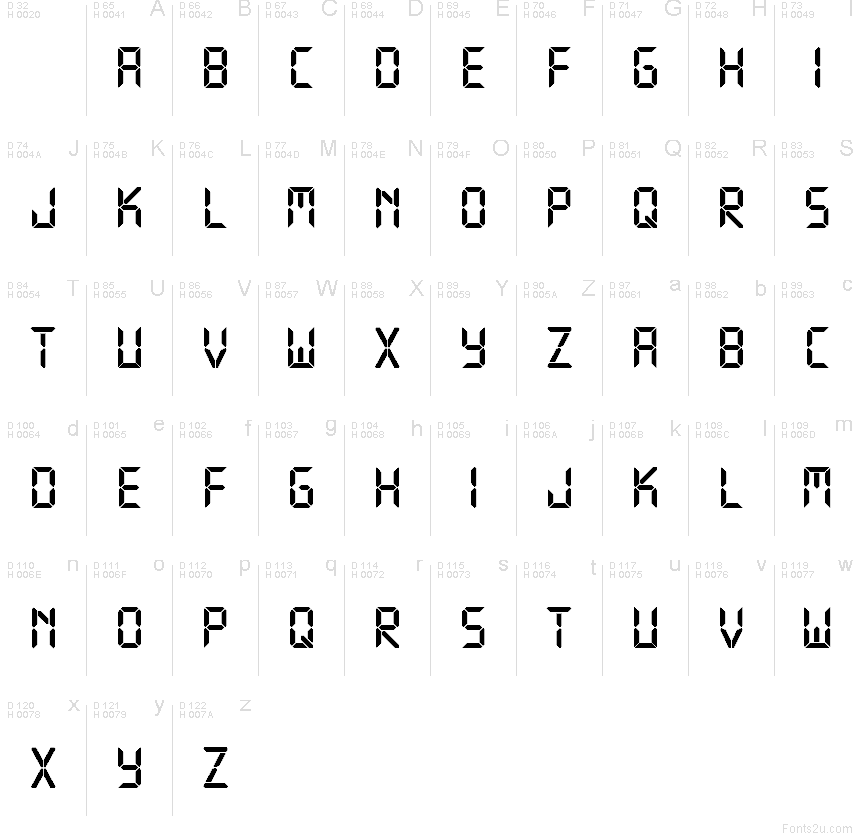
Technology Extravagant di Vladimir Nikolic è un font display digitale gratuito che richiama le forme dei display LED segmentati. Grazie agli angoli smussati e alle sezioni delle barre separate, ogni lettera si trasforma in un pattern di segnale compatto. Questa struttura ripetitiva conferisce al carattere un ritmo nitido e tecnico, che ricorda più dei moduli luminosi assemblati che una classica scritta sans serif.
È perfetta per poster sci-fi, titoli in stile arcade, grafiche per dashboard, volantini di eventi tecnologici e mockup di interfacce, dove questa logica segmentata comunica molto più di un semplice font. I titoli brevi e le indicazioni numeriche sono i contesti in cui rende al meglio, donando alle etichette e al branding un carattere elettronico preciso e studiato.
Technology Extravagant è disponibile in quattro stili: Regular, Italic, Bold e Bold-Italic.